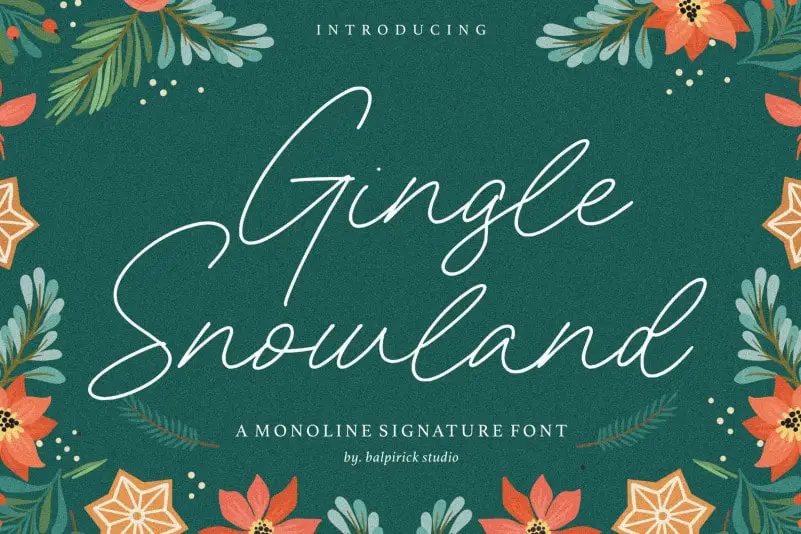
Gingle Snowland Monoline Signature Font – Download Grátis
A “Gingle Snowland Monoline Signature Font” é uma criação originalmente projetada para quem busca uma fonte elegante e versátil. Suas linhas simples e delicadas têm um toque único que a torna perfeita para criar design de marca ou embalagens de produto, especialmente quando você quer destacar seu texto acima do fundo. Seja para aplicar em revistas, redes sociais, projetos de casamento ou mesmo apenas para expressar palavras no topo de um fundo, esta fonte oferece uma experiência visual sofisticada e moderna. Suas linhas clean e sutis podem ser usadas com facilidade em diversos formatos, garantindo que seu design sempre permaneça impecável. A Gingle Snowland Monoline Signature Font é uma escolha inteligente para designers buscando um elemento distintivo e elegante para seus trabalhos de arte final.